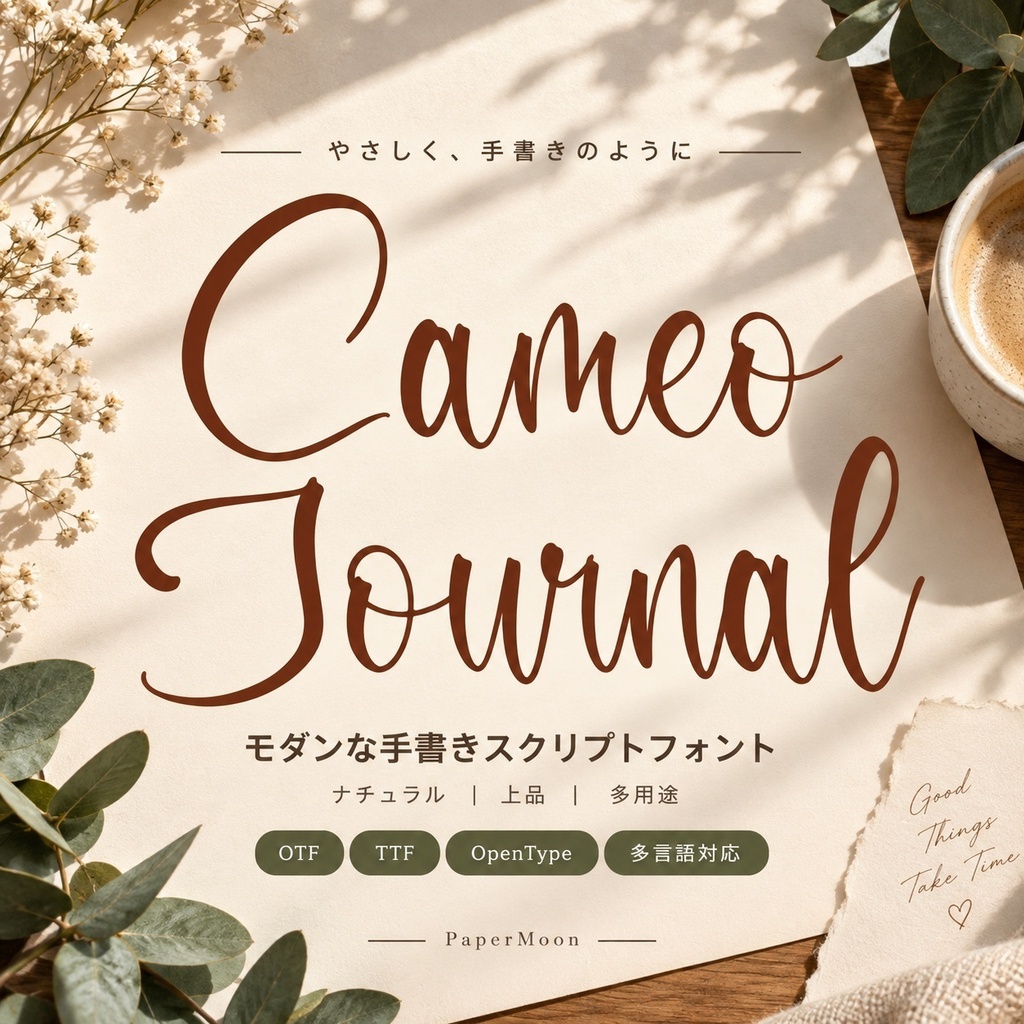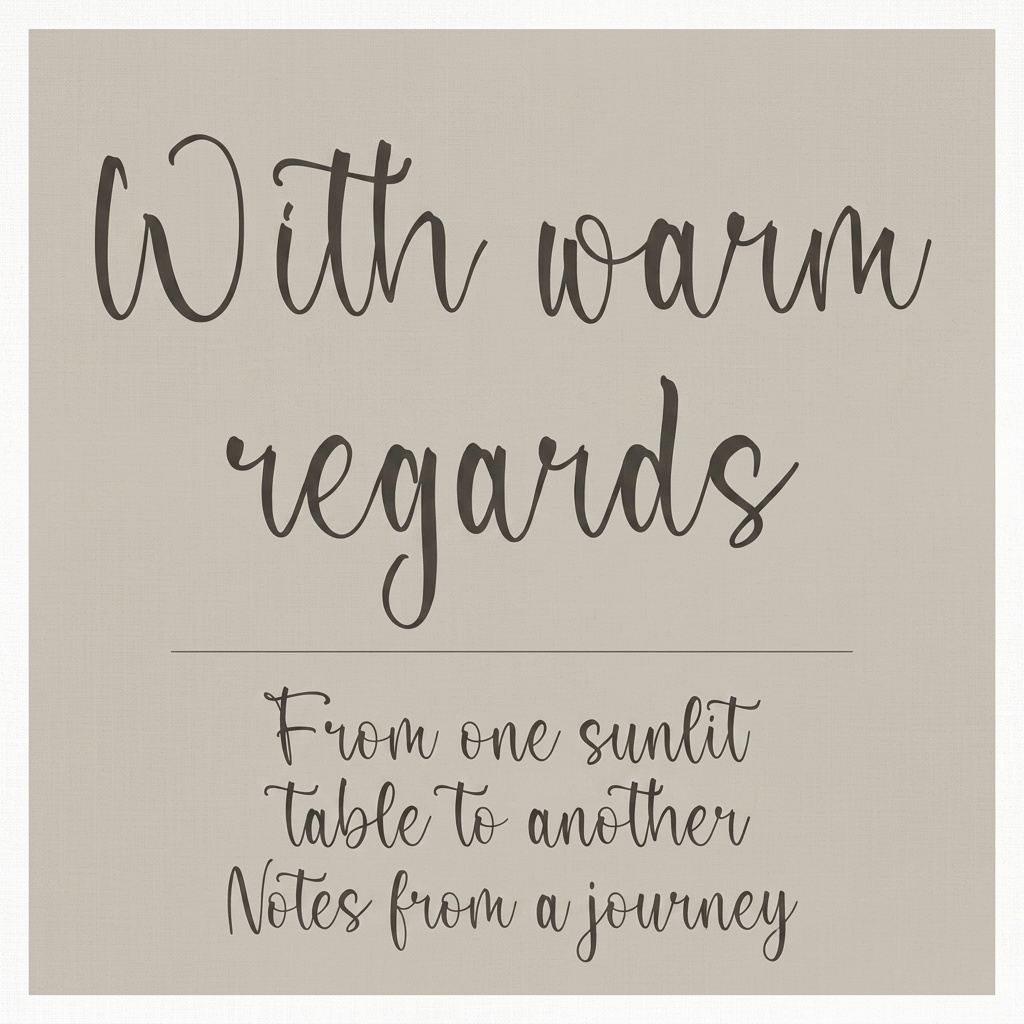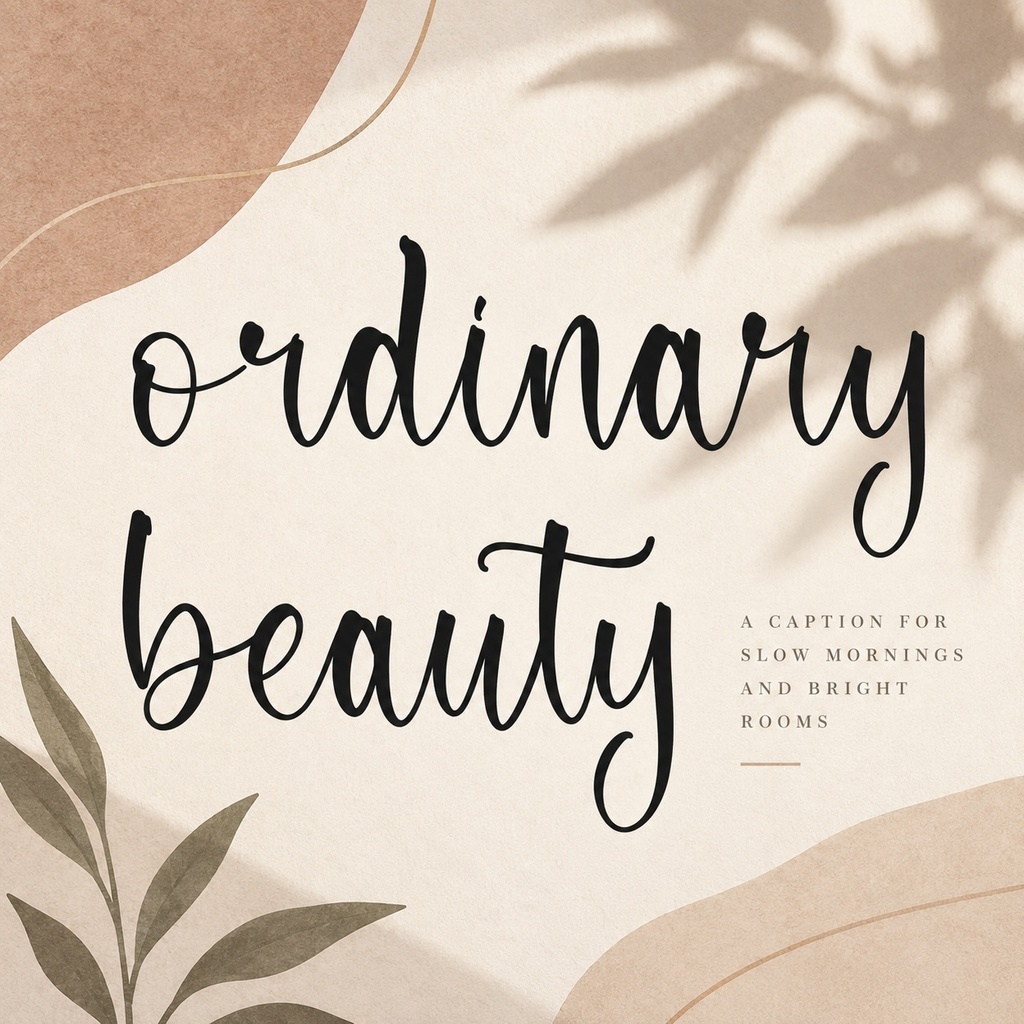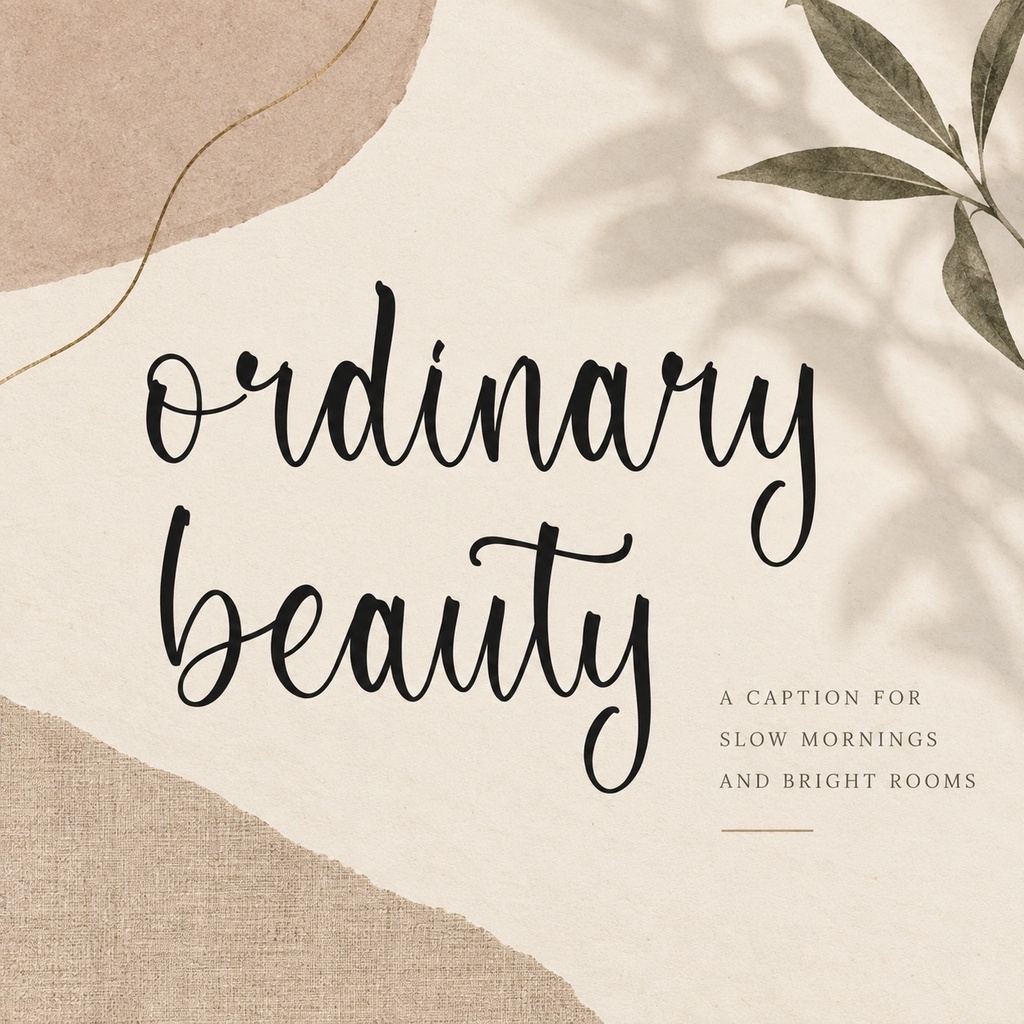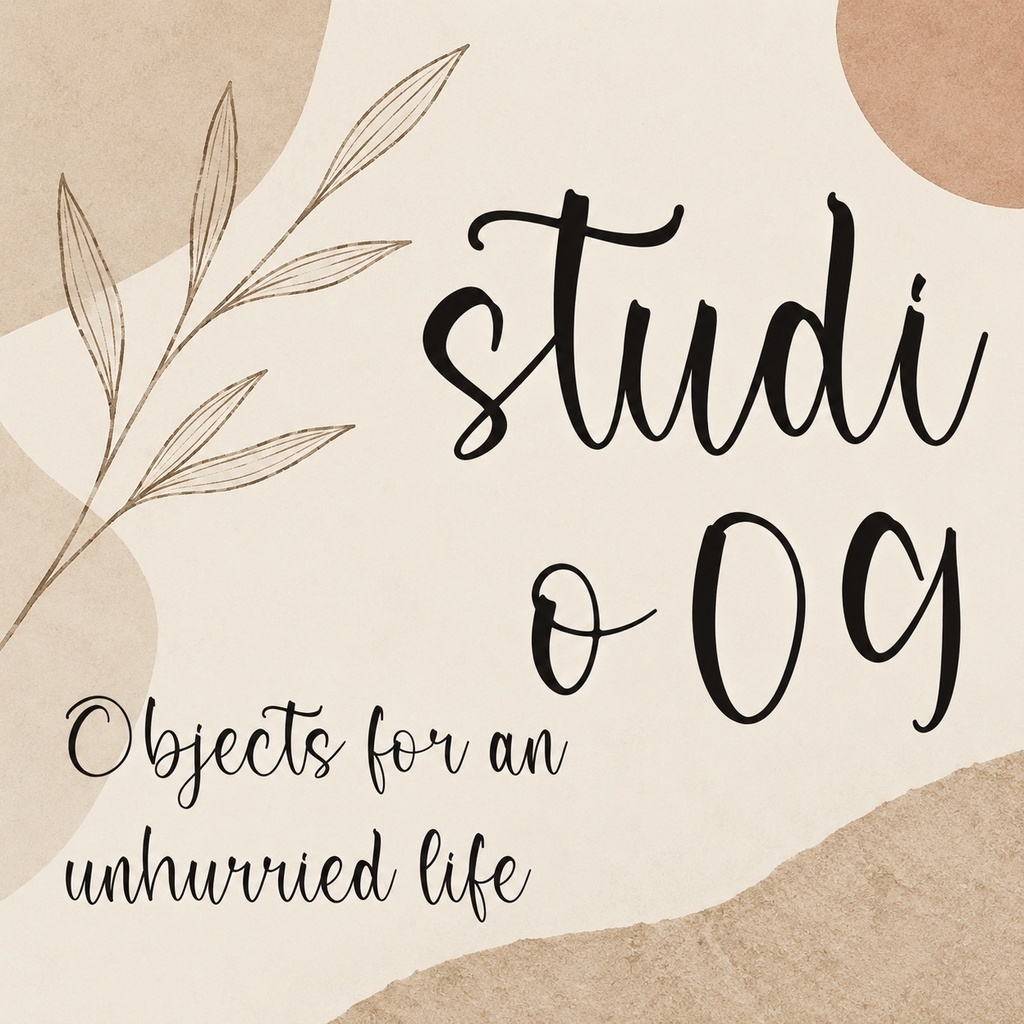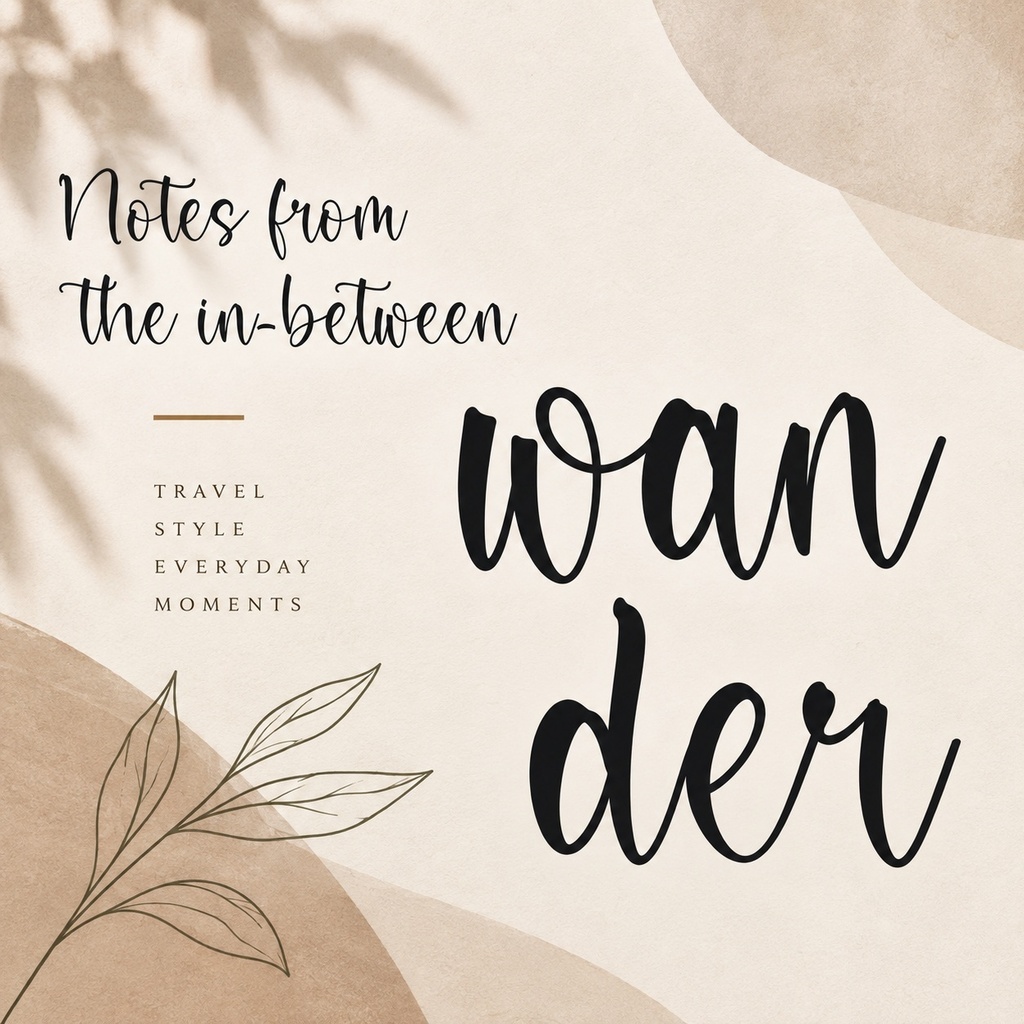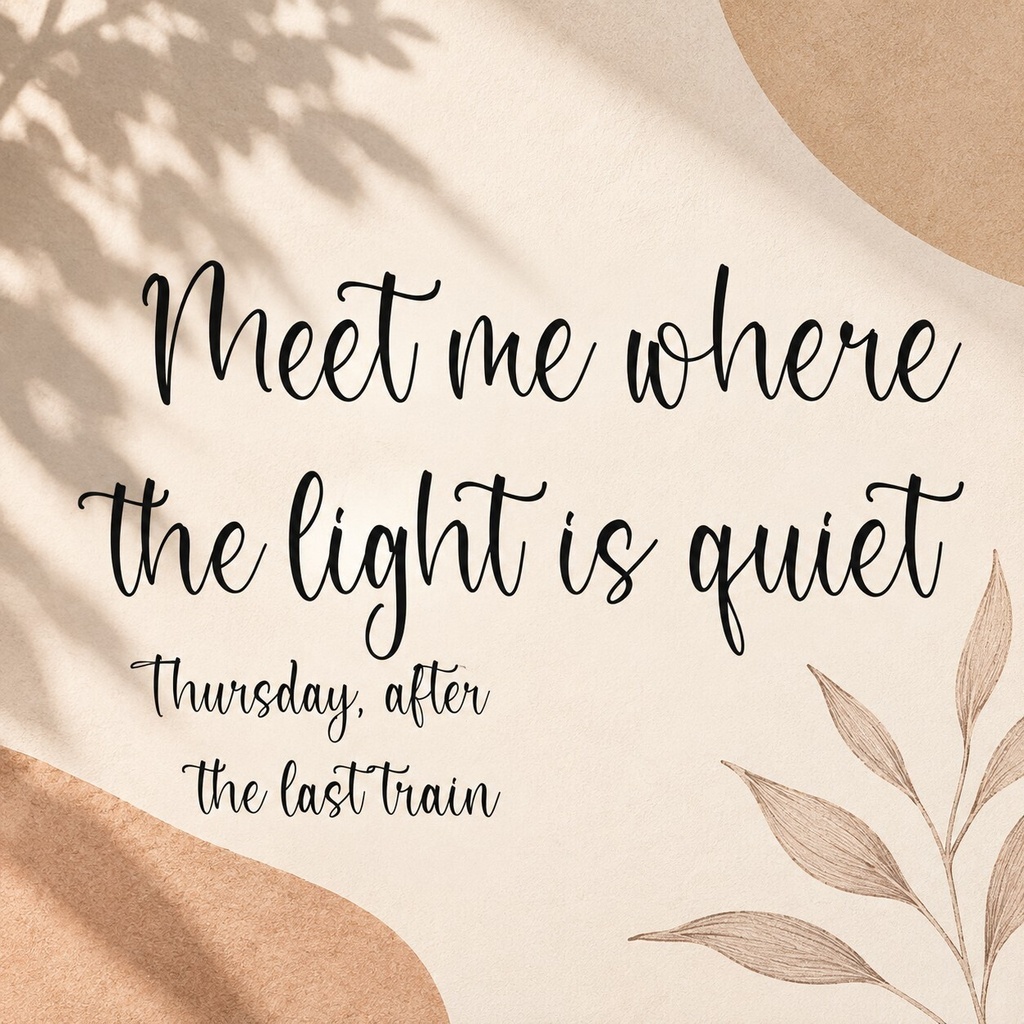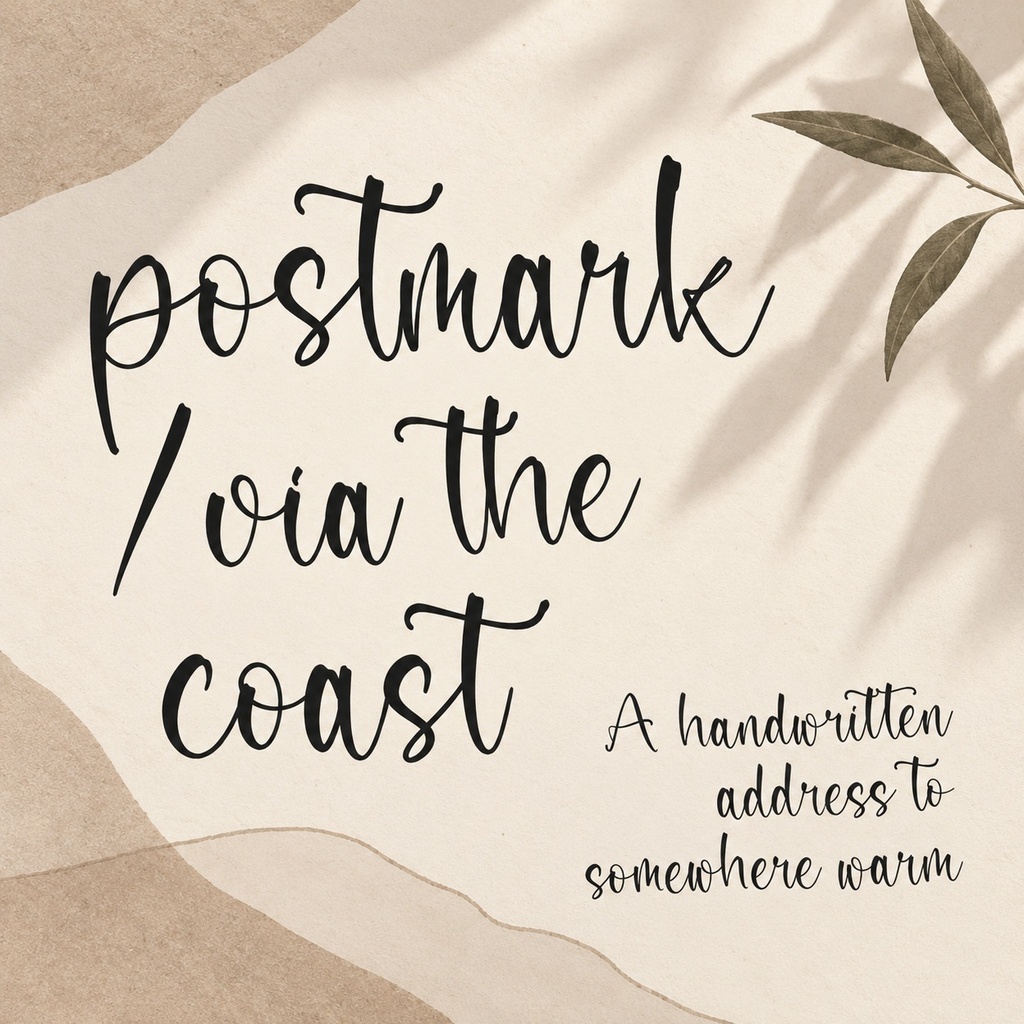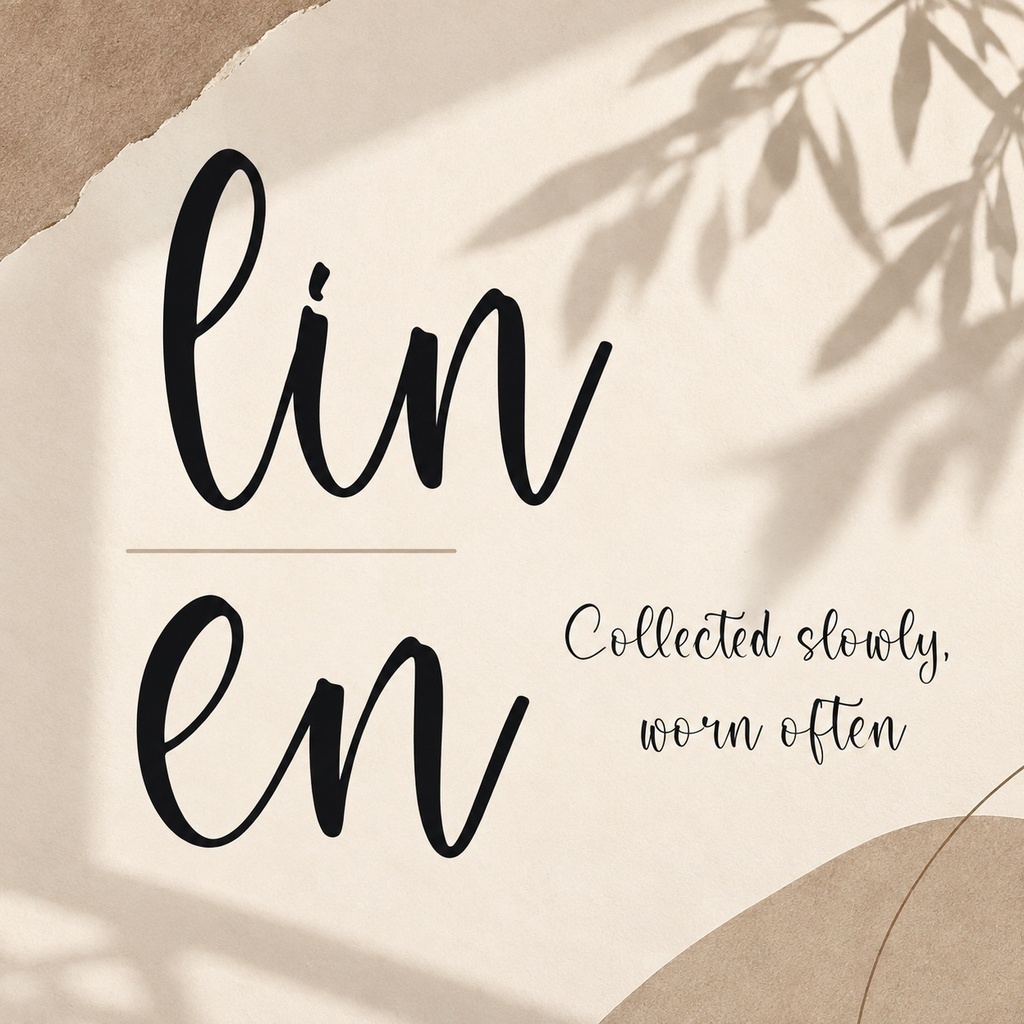
Cameo Journal | 手書き筆記体の欧文フォント | ロゴ・ブランディング向け
自然な手書きの流れと洗練された表情で、Cameo Journalはロゴやブランディング、招待状を印象的に仕上げる手書きフォントです。 繊細な筆記体のリズムに、ヨーロッパの旅の便りや静かなブティックのエディトリアルを思わせる落ち着いた雰囲気を添えています。ソーシャルメディア用の画像、ウェブサイトの見出し、ショップやファッションの文字表現、ステーショナリー、旅行の correspondence に自然になじみます。 収録内容 Regular、Italicの2スタイルを収録しています。文字の印象を調整できるalternative characters、ligatures、swashesを備えています。 対応文字 国際的な文字表現に対応するmultilingual charactersを収録しています。詳しい収録範囲は購入前に文字見本でご確認ください。 用途 ロゴ、ブランディング、招待状、ソーシャルメディア用コンテンツ、ウェブサイトの見出し、 merchandise、ファッションやエディトリアルのステーショナリー、旅行の便りにご利用いただけます。流れる筆記体の個性を活かしたタイトルや短いメッセージにも向いています。 形式 OpenType(OTF)、TrueType(TTF)、Webフォント用(WOFF、WOFF2)を収録しています。 対応環境 OTF、TTFは対応するデザイン・文書作成ソフトでご利用ください。WOFF、WOFF2はWebフォントに対応した環境でご利用ください。ソフトウェアごとのalternative characters、ligatures、swashesの表示方法は各ソフトの仕様をご確認ください。 利用許諾 商用利用・個人利用の具体的な許諾範囲、再配布、再販売、埋め込み、テンプレート利用の条件は、販売設定およびライセンス案内をご確認ください。未確定の許諾事項は [LICENSE FACTS TO CONFIRM] として seller entry で確認してください。 旧名称 Scottmid Blissful から改名したフォントです。旧名称の記載が必要な制作物では、購入記録とあわせてご確認ください。